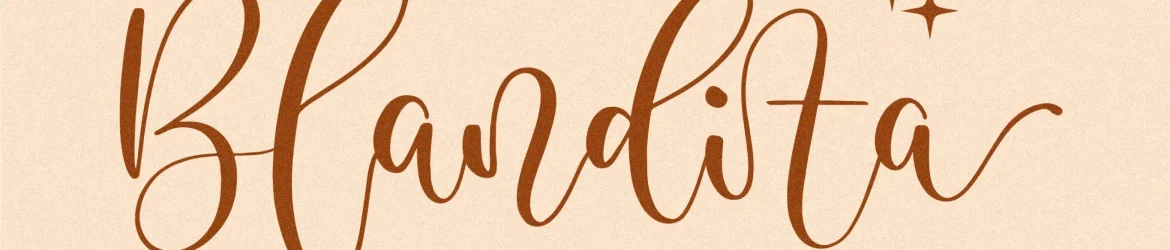
Blandita Font – Fonte Grátis
Blandita Font
Blandita Font é uma elegante tipografia romântica projetada para criar mensagens memoráveis. Suave e delicada, esta fonte idealmente se adapta a diversas áreas de aplicação incluindo logotipos, projetos de marca, designs de móveis de consumo, embalagens de produtos, copos personalizados, cartões de citação, convites, cards de cumprimento, etiquetas e mais. Suas linhas perfeitas são uma escolha perfeita para qualquer projeto que deseja agregar um toque delicado e único aos seus designs. Seja em uma camiseta ou em um livro, a Blandita Font trará um quê de sofisticação e romantismo para sua criação. Ideal tanto para designers iniciantes quanto experientes, esta fonte é uma ótima opção para aqueles que desejam dar um toque especial aos seus projetos.